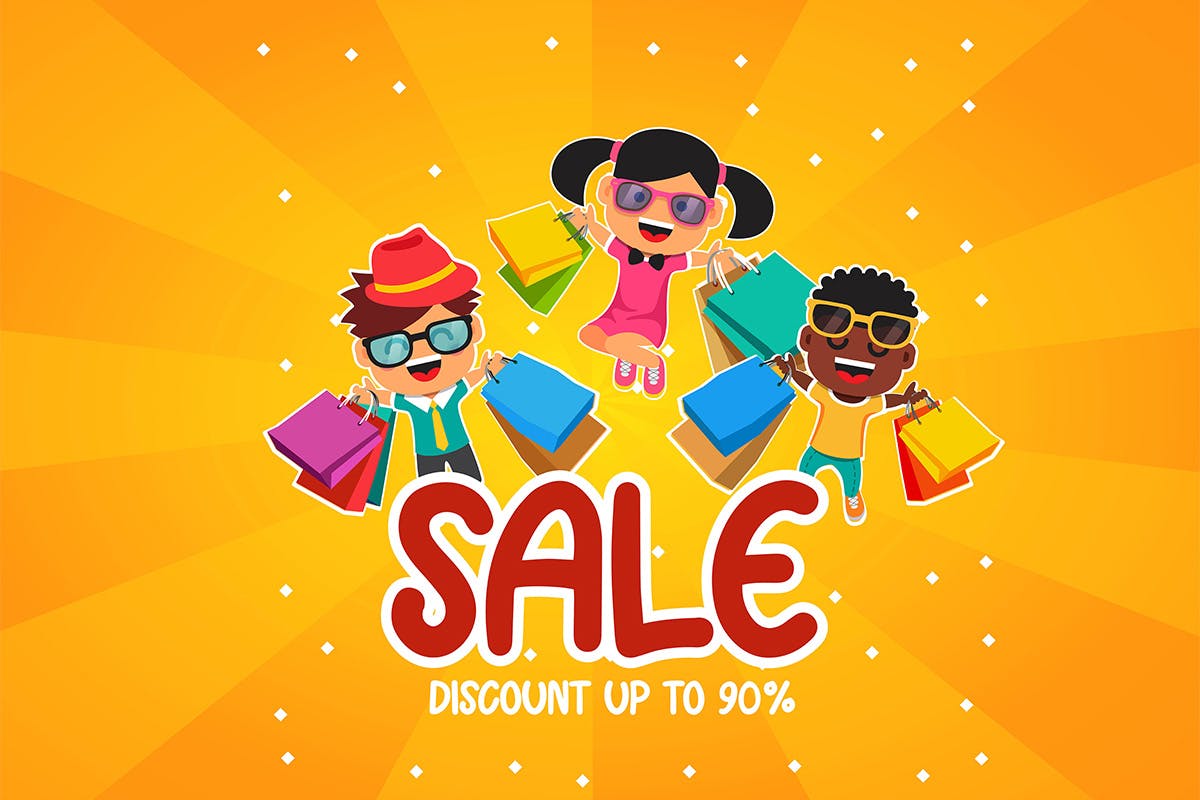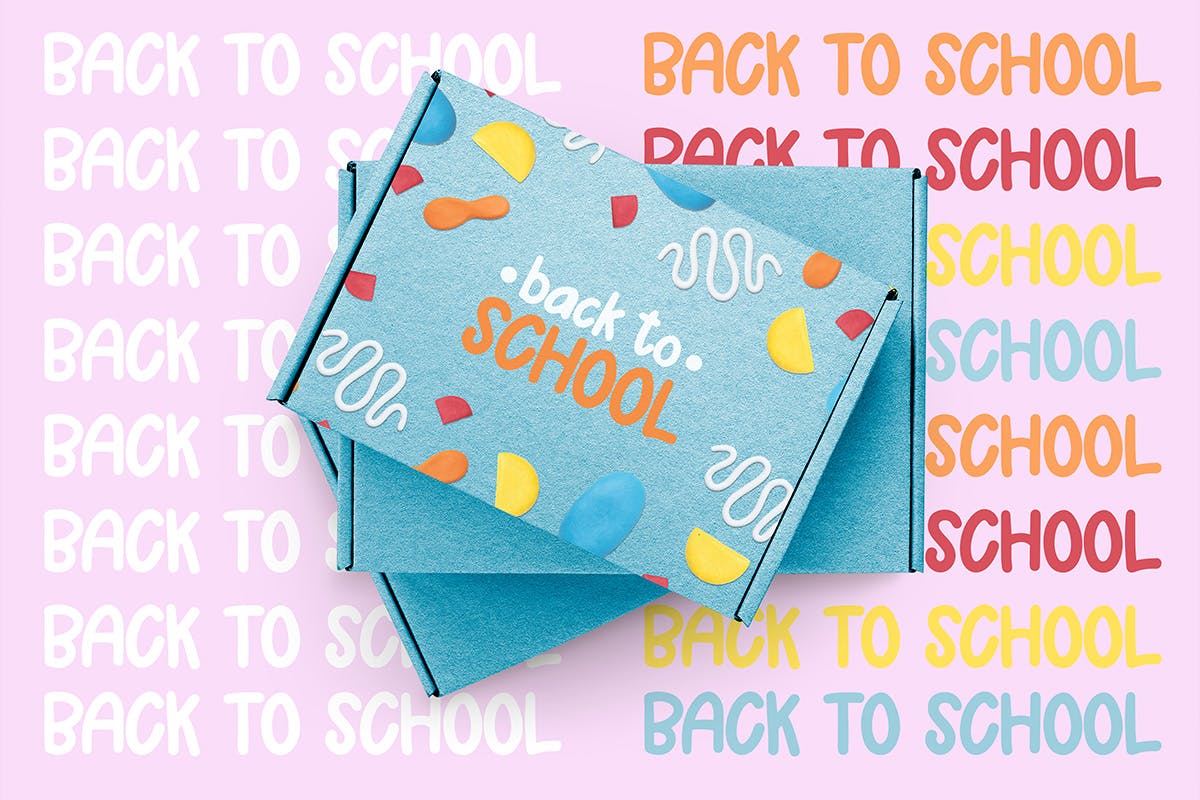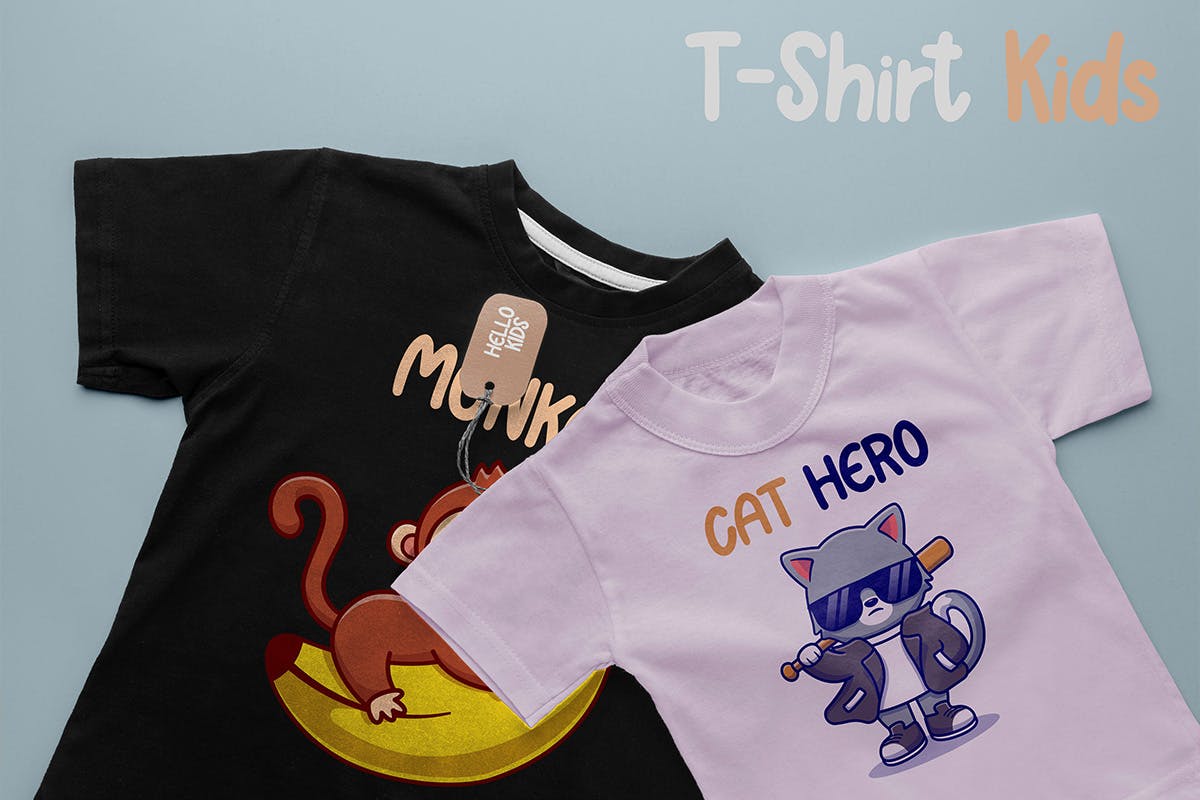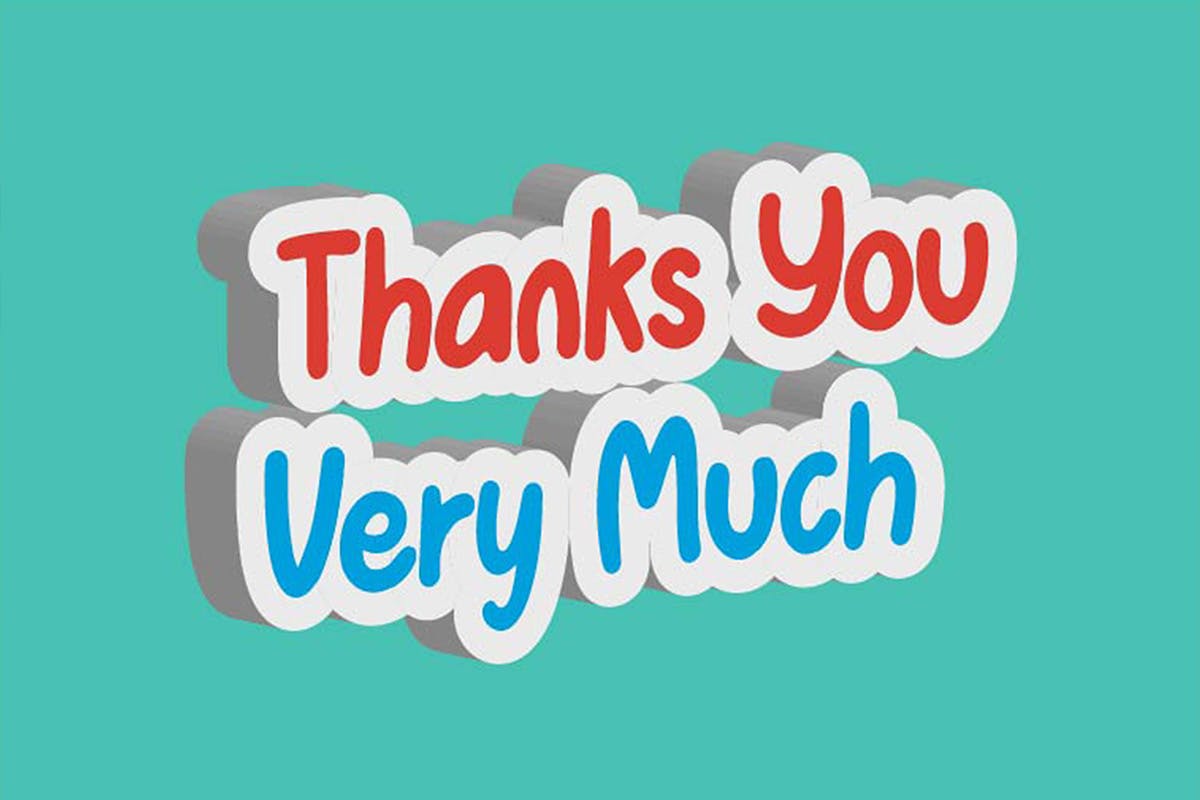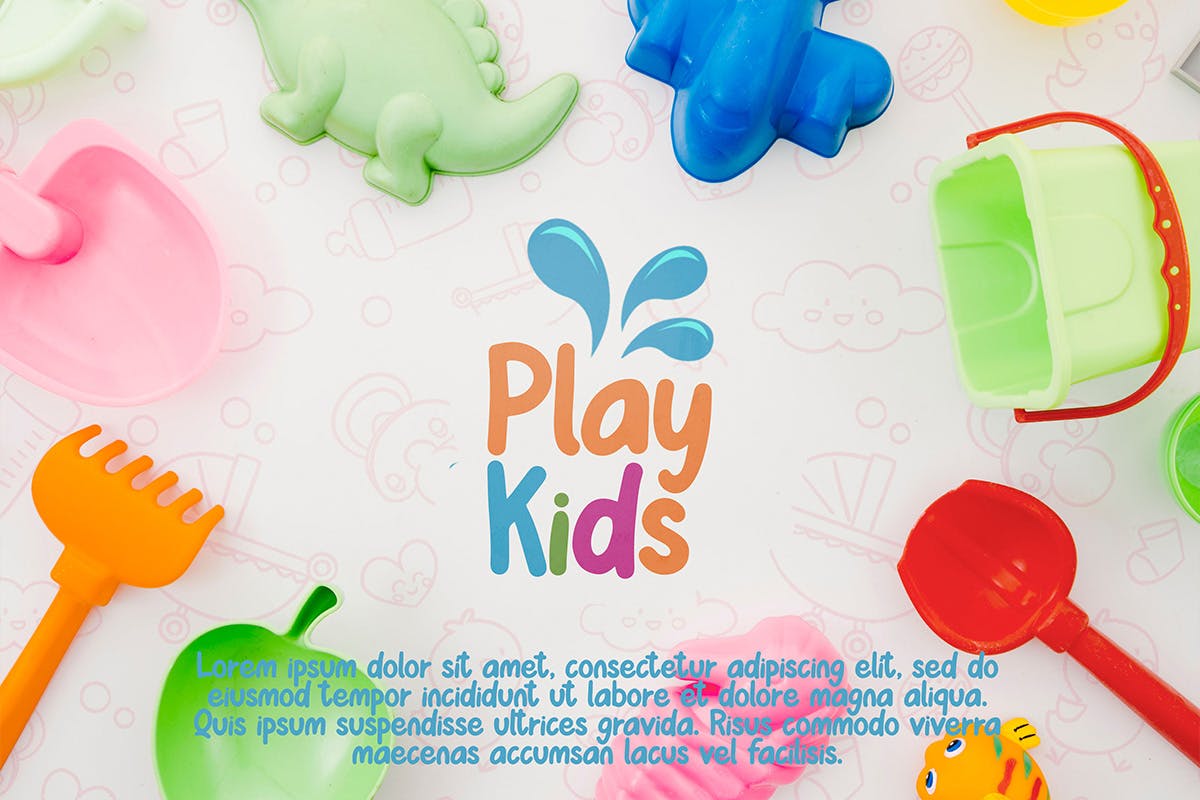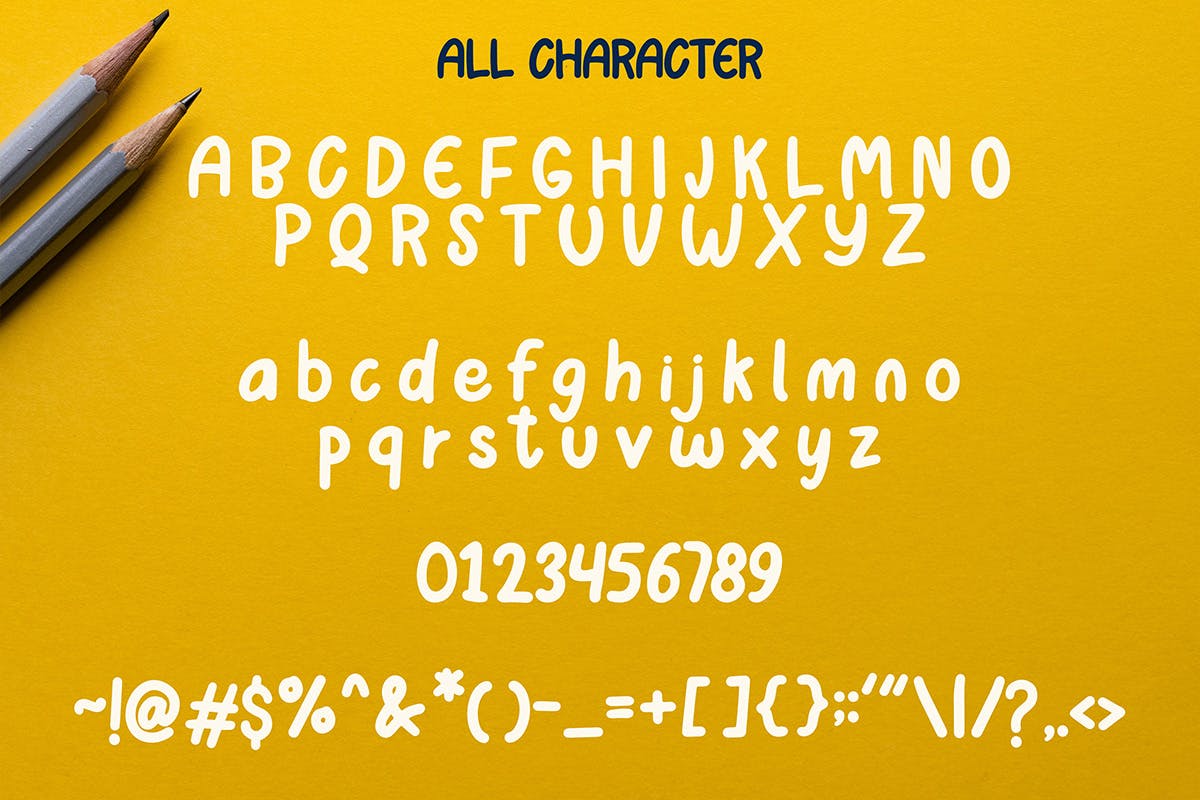
دانلود فونت دست‌نویس Choco Donut زیبا و دوستانه
Choco Donut Handwritten Font
فونت Choco Donut، انتخابی عالی برای طراحی‌های خلاقانه شما!
فونت Choco Donut یک فونت دست‌نویس ساده، دوستانه و زیبا است. این فونت برای طراحی‌های مختلف از جمله کارهای دستی، طراحی دیجیتال، ارائه‌ها و ساخت کارت‌های تبریک بسیار مناسب است!
• قابل استفاده در پروژه‌های مختلف طراحی
• مناسب برای طراحی‌های خلاقانه و جذاب
• ایجاد حس دوستانه و صمیمی در متن‌ها